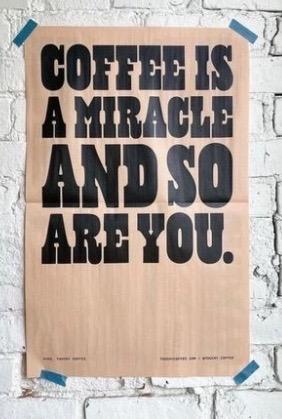
Was ist denn das für eine hübsche Egyptienne?
Das ist wohl eher ein Computerfont als eine Holzletter - vermute ich mal. Weiß jemand hier, wie die Schrift heißt und von wem sie ist? Danke für alle sachdienlichen Hinweise!